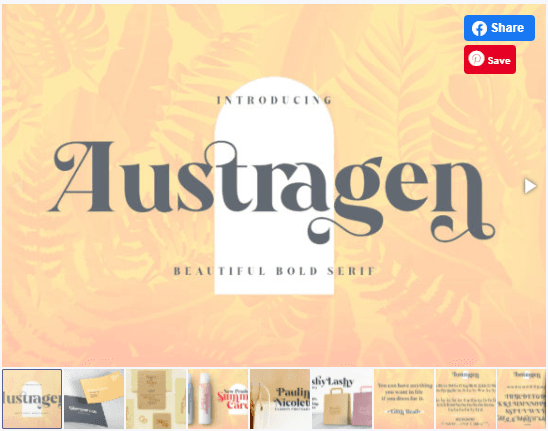
Austragen Font
Austragen - модный жирный шрифт с засечками. Он имеет стильный вид, который можно использовать для логотипов, брендинга, приглашений, канцелярских принадлежностей, свадебных дизайнов, сообщений в социальных сетях и многого другого!
Этот шрифт имеет кодировку PUA, что означает, что вы можете легко получить доступ ко всем красивым глифам и росчеркам!